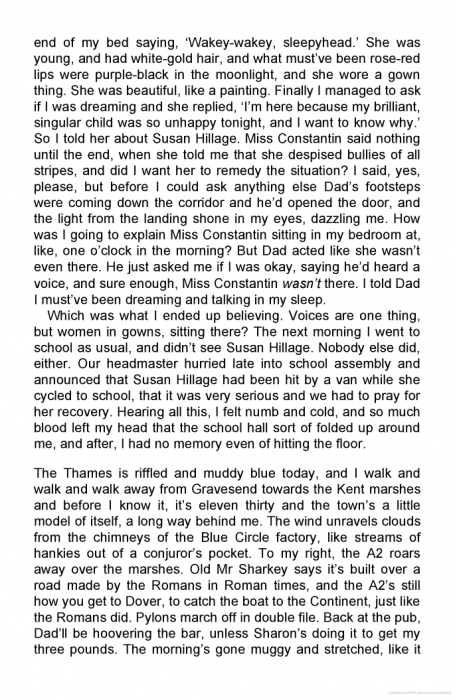
Wann setzt man drei Sternchen, wann einen Abstand zwischen Absätzen?
Manchmal gibt es in erzählenden Prosatexten eine Lücke zwischen Absätzen. Die gewöhnlichen Formen sind eine Reihe von drei Sternchen (alternativ eine kurze Linie oder ein Ornament) oder eine Leerzeile.
Unterscheiden sich beide Formen hinsichtlich ihrer Bedeutung?
Manchmal benutzen Bücher beide Formen, dann scheint mir der Unterschied folgender zu sein:
Drei Sternchen
Bezeichnen eine zeitliche Lücke.
Zwischen den beiden durch drei Sternchen getrennten Textteilen ist Zeit vergangen, der Ort der Handlung und die Hauptfigur bleiben jedoch gleich. In der Pause hat der Protagonist beispielsweise geschlafen, war arbeiten oder hat etwas anderes, wenig berichtenswertes erledigt.
Beispiel:
"Ich geh schlafen." Beate schlurfte hinaus.
Ich setzte die Brille wieder auf und las weiter.
* * *
Es war still, nur Beates ruhiges Atmen war zu hören. Ich wünschte, sie würde nicht immer so früh schlafen gehen. Ich fühlte mich einsam, wenn ich nachts alleine im Wohnzimmer saß.
Leerzeile
Bezeichnet einen Ortswechsel und/oder einen Wechsel zur Erzählperspektive eines anderen Protagonisten.
Beispiele:
"Ich geh schlafen." Beate schlurfte hinaus.
Ich setzte die Brille wieder auf und las weiter.
Warum muss Henning nur jeden Abend noch stundenlang lesen? Ich wünschte, er würde gemeinsam mit mir zu Bett gehen. Ich schaltete das Licht im Badezimmer ein und sah in den Spiegel. Lag es an mir, dass er sich von mir zurückzog?
oder:
"Ich geh schlafen." Beate schlurfte hinaus.
Ich setzte die Brille wieder auf und las weiter.
Die Luft stand heiß und unbeweglich in den Häuserschluchten San Franciscos. Frank sah auf die Uhr. Ob Henning noch wach war? Er nahm sein Handy und wählte Hennings Nummer.
Entspricht das eurer Beobachtung, und gibt es eigentlich Regelwerke, die die korrekte Verwendung dieser Formatierungen erklären?
Ich würde mich insbesondere über Quellenangaben freuen.
schau mal hier: http://www.typografie.info/3/page/wiki.html/_/fachbegriffe/abteilungssternchen-r211
ich würde mal sagen, solch ein Abteilungssternchen dient schon der logischen Trennung all der betroffenen Aspekte innerhalb einer sonst eigenständigen Geschichte, was genau dann gemeint ist, ergibt sich dannn aus dem kontext.
Ein einfach etwas breiterer Absatzabstand könnte ja auch nur dadurch erforderlich gewesen sein, um einen Schusterjungen auf die nächste Seite zu schieben, ist aber eben trotzdem "nur" ein normaler Absatz.
Ich bezweifle, dass es hier irgendwer mal Regeln, wie Du sie suchst, festgehalten hat. Selbst wenn, zwingen dich schlimmstenfalls die obskuren Richtlinien eines Verlags, Dich daran zu halten.
Das Einzige, was mir diesbezüglich über den Weg gelaufen ist, ist, dass eine Unterteilung, die normalerweise mit einer Leerzeile gekennzeichnet würde, mit drei Sternchen gekennzeichnet wird, wenn sie auf einen Seitenumbruch fällt (da man sie sonst nicht erkennen könnte).
Ein einfach etwas breiterer Absatzabstand könnte ja auch nur dadurch erforderlich gewesen sein, um einen Schusterjungen auf die nächste Seite zu schieben, ist aber eben trotzdem "nur" ein normaler Absatz.
catfonts, hier ist beispielhaft eine Seite aus David Mitchell, The Bone Clocks, die zeigt, dass eine Leerzeile auch mitten in der Seite vorkommen kann (neben anderen, eng gesetzten Absätzen) und ganz sicher nichts mit Schusterjungen zu tun hat.
natürlich hat die jetzt nichts mit dem schusterjungen zu tun, sondern ist schlicht bein absatz, ich meine ja, wenn solch eine lücke mal etwas breiter erscheint, als sonst im buch, muss das nicht unbedingt etwas mit der erzähllogik zu tun haben.
Wenn bei Absätzen grundsätzlich keine Leerzeile eingeteilt ist, bei einigen Absätzen aber „ausnahmsweise“ eingeteilt wird, so hat dies entweder mit der Erzähllogik zu tun oder es wurde fälschlicherweise vom Setzer eingeteilt.
Es liegt im Ermessen des Autors, ob er bei einigen speziellen Absätzen eine Leerzeile, Sternchen oder sonst ein Zeichen dazwischen möchte, um eben dem Leser zu vermitteln, dass hier eine Schnittstelle, eine Pause oder sonst etwas anders ist, als nach den üblichen Absätzen.